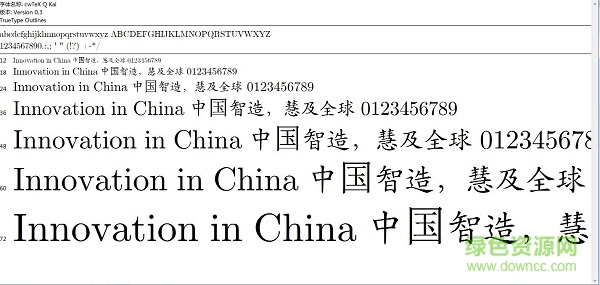
cwtex中文字體是一款易讀性比較高的襯線字體,字體結(jié)構(gòu)平穩(wěn),空隙均勻,具有獨(dú)特沉穩(wěn)的氣質(zhì),常常用于正文內(nèi)容內(nèi),閱讀效果好,喜歡的朋友快來(lái)下載吧吧!
中文字體中的宋體就是一種最標(biāo)準(zhǔn)的serif字體,襯線的特征非常明顯。字形結(jié)構(gòu)也和手寫(xiě)的楷書(shū)一致。因此宋體一直被做為最適合的正文字體之一。不過(guò)由于強(qiáng)調(diào)橫豎筆畫(huà)的對(duì)比,在遠(yuǎn)處觀看的時(shí)候橫線就被弱化,導(dǎo)致識(shí)別性的下降。
襯線增加了閱讀時(shí)對(duì)字母的視覺(jué)參照。而無(wú)襯線字體往往被用在標(biāo)題、較短的文字段落或者一些通俗讀物中。